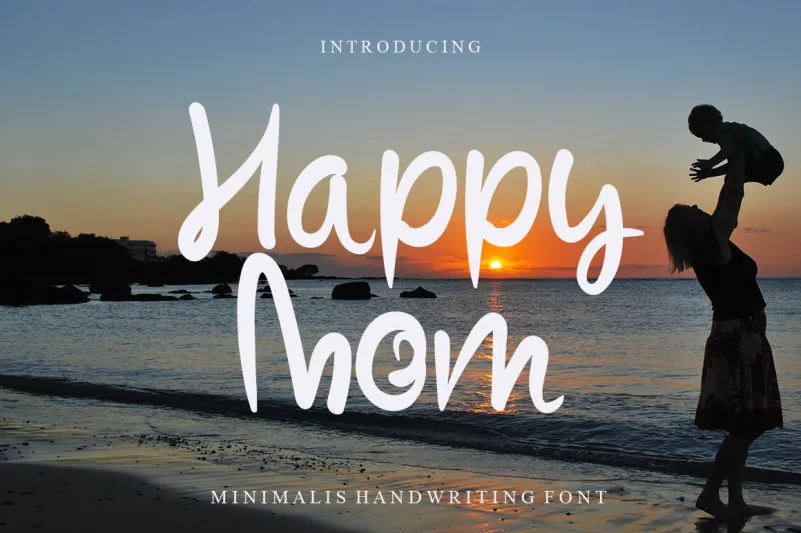
Happy Mom Font – Fonte Grátis
Happy Mom Font
A fonte Happy Mom é perfeita para designers que procuram uma mão-dura escrita curvilínea com um toque natural e autêntico. Inspirada na caligrafia carente, essa elegante fonte traz um toque suave que se adapta a diversos ideias de design, seja ela em cartazes publicitários, gráficos de newsletter ou mesmo em títulos no site. Seu charme delicado e sua natureza genuína podem ser adicionados à qualquer projeto para dar-lhe uma pitada de júbilo e romantismo. Ideal tanto para uma atmosfera romântica como para um design mais leve, a Happy Mom é uma fonte que certamente fará você se sentir feliz ao trabalhar com ela.